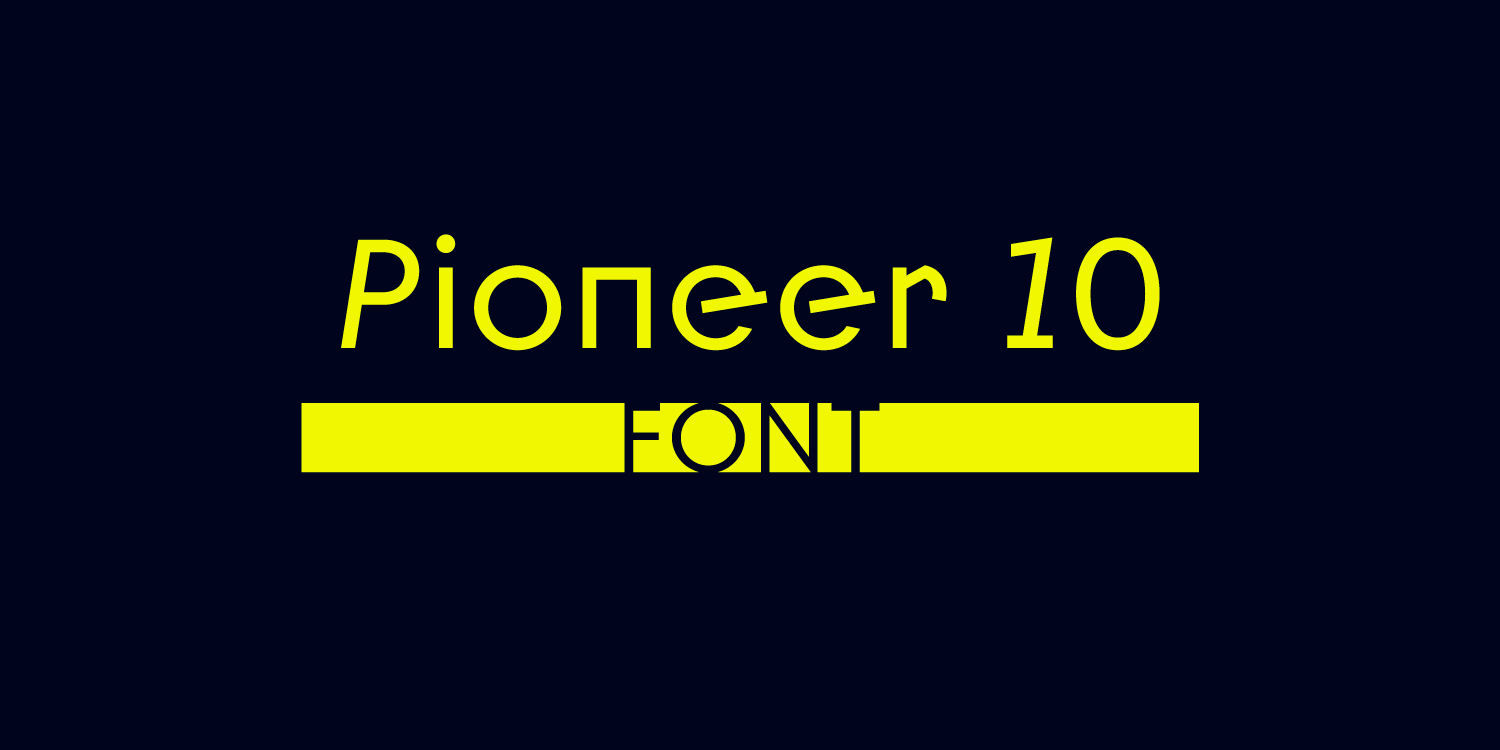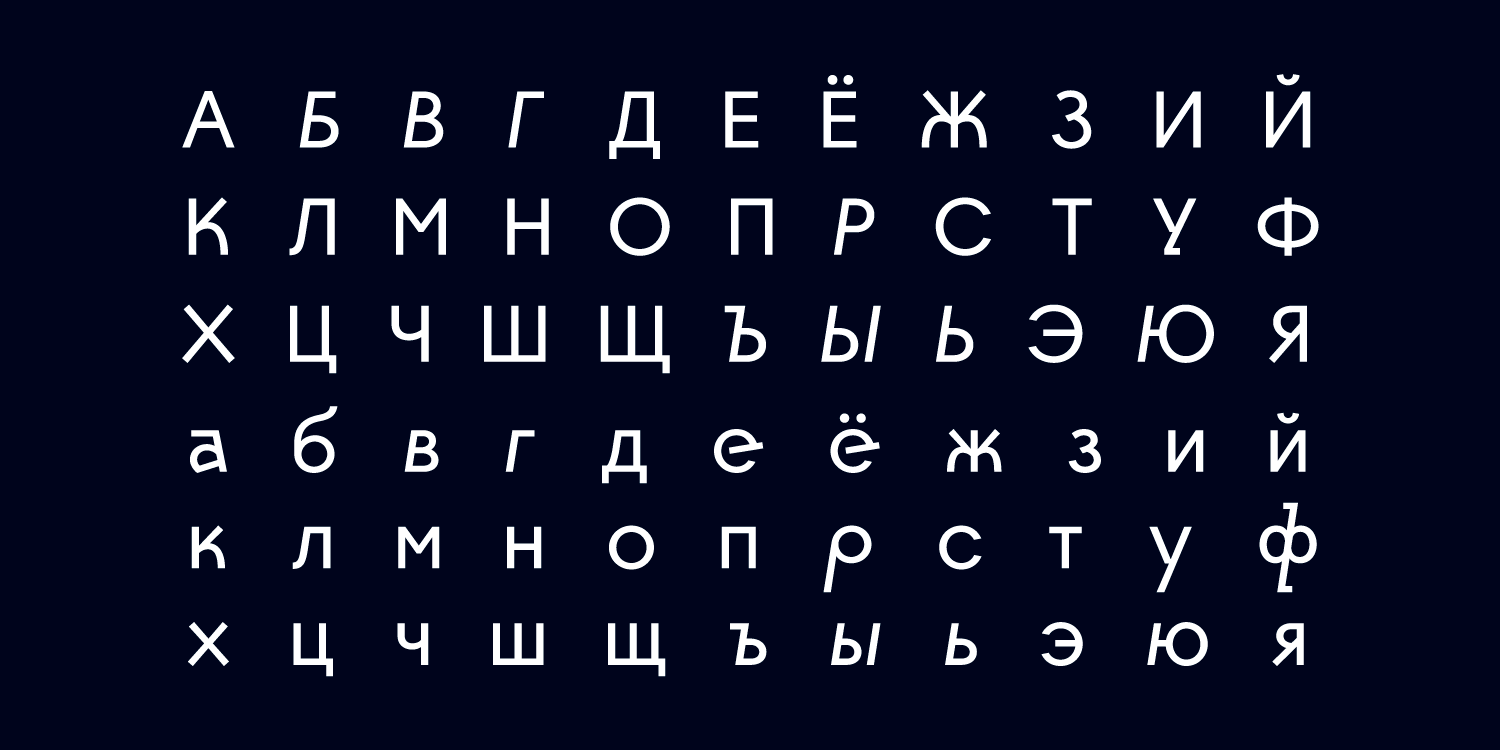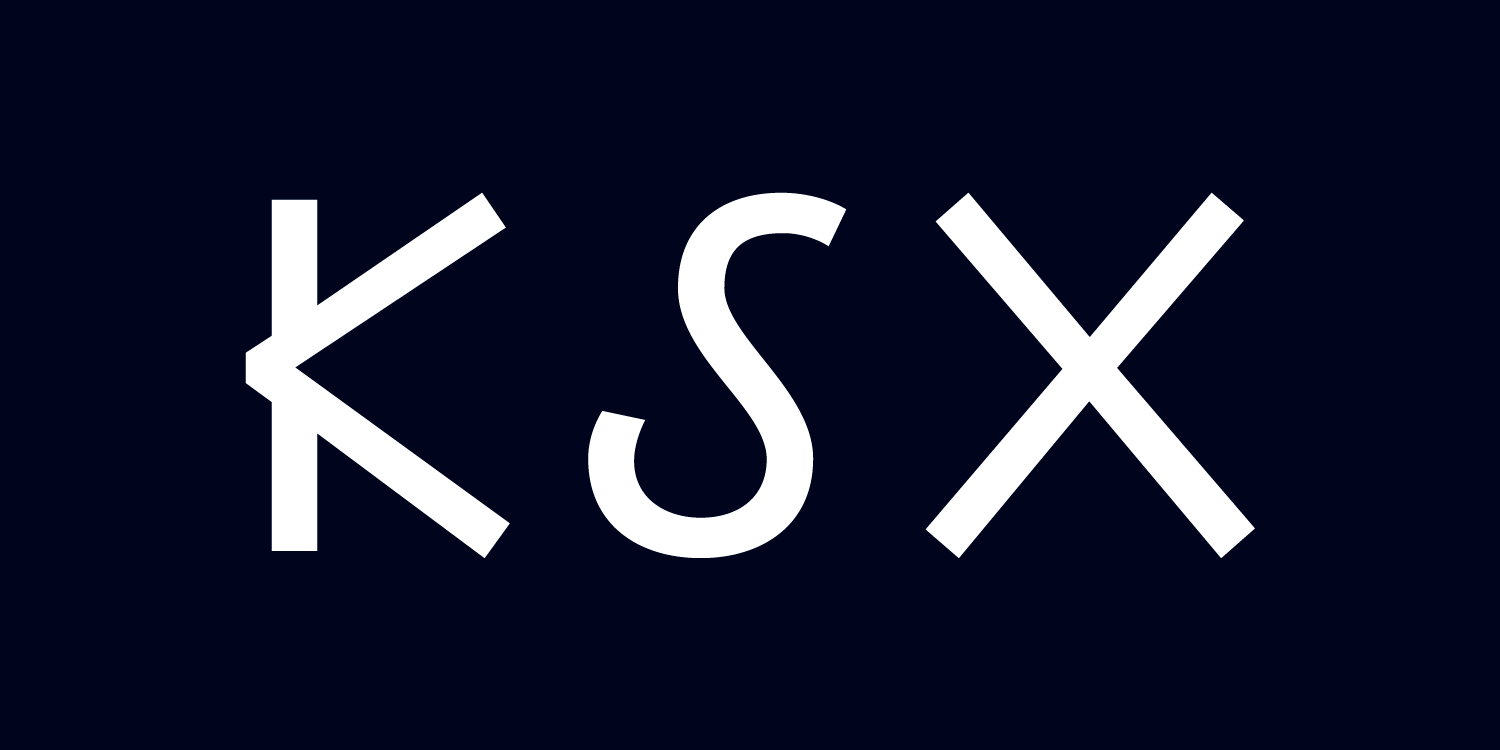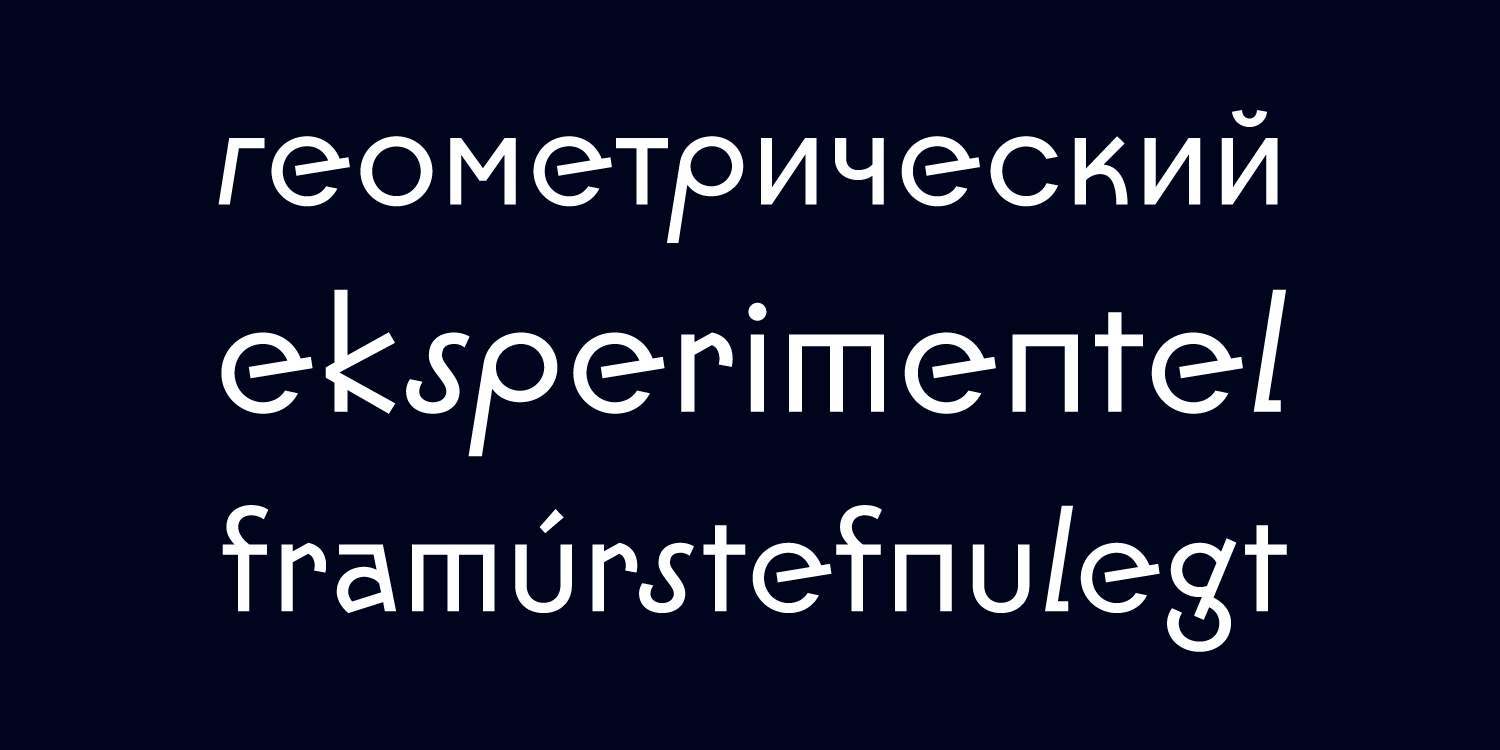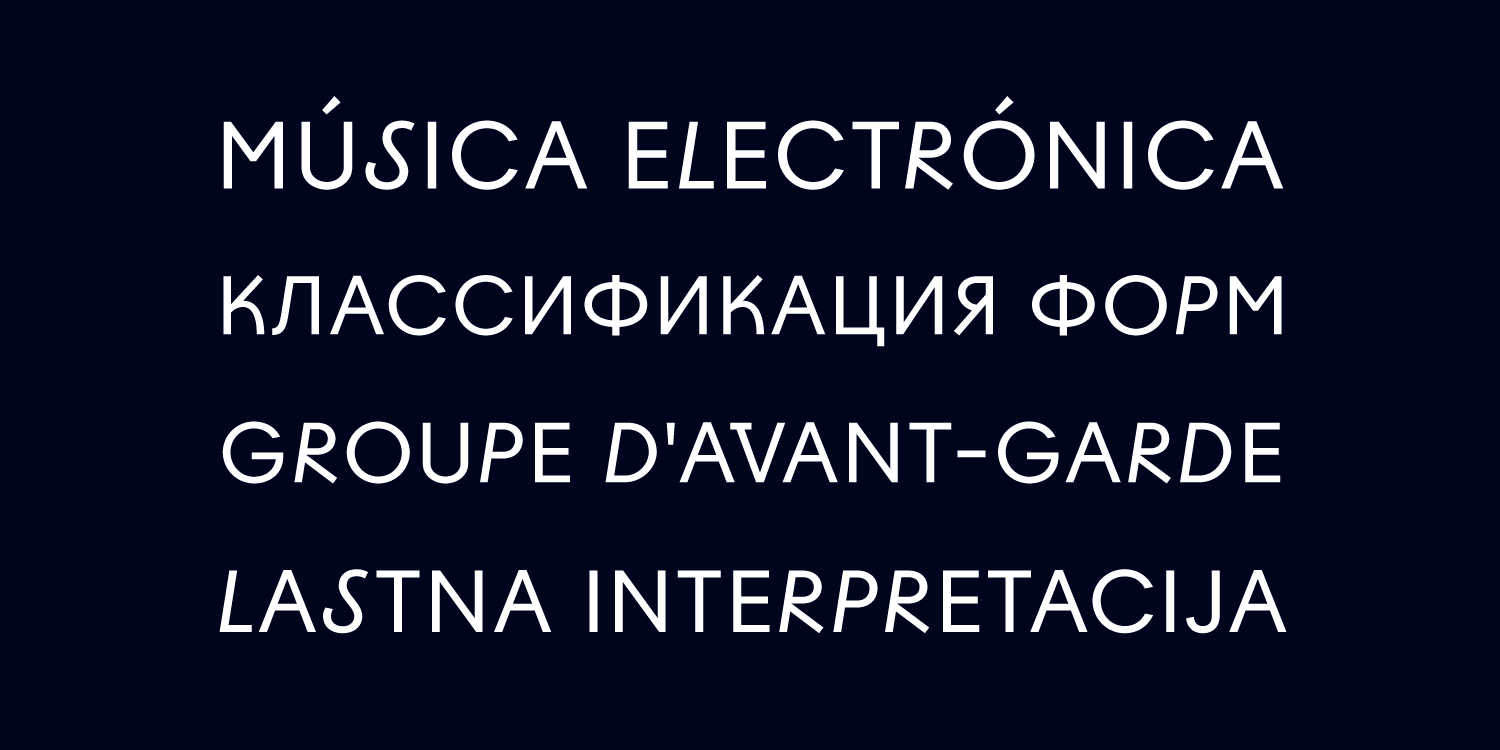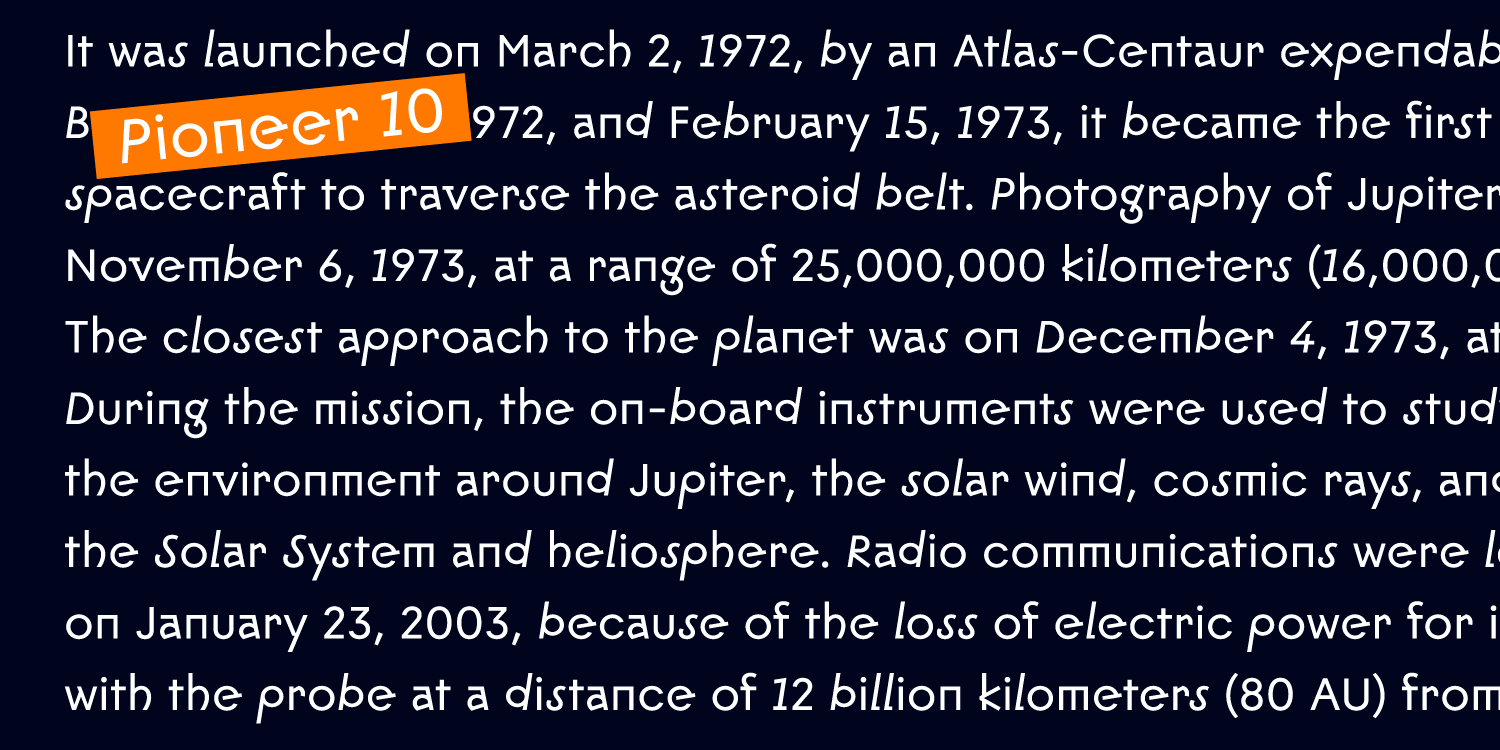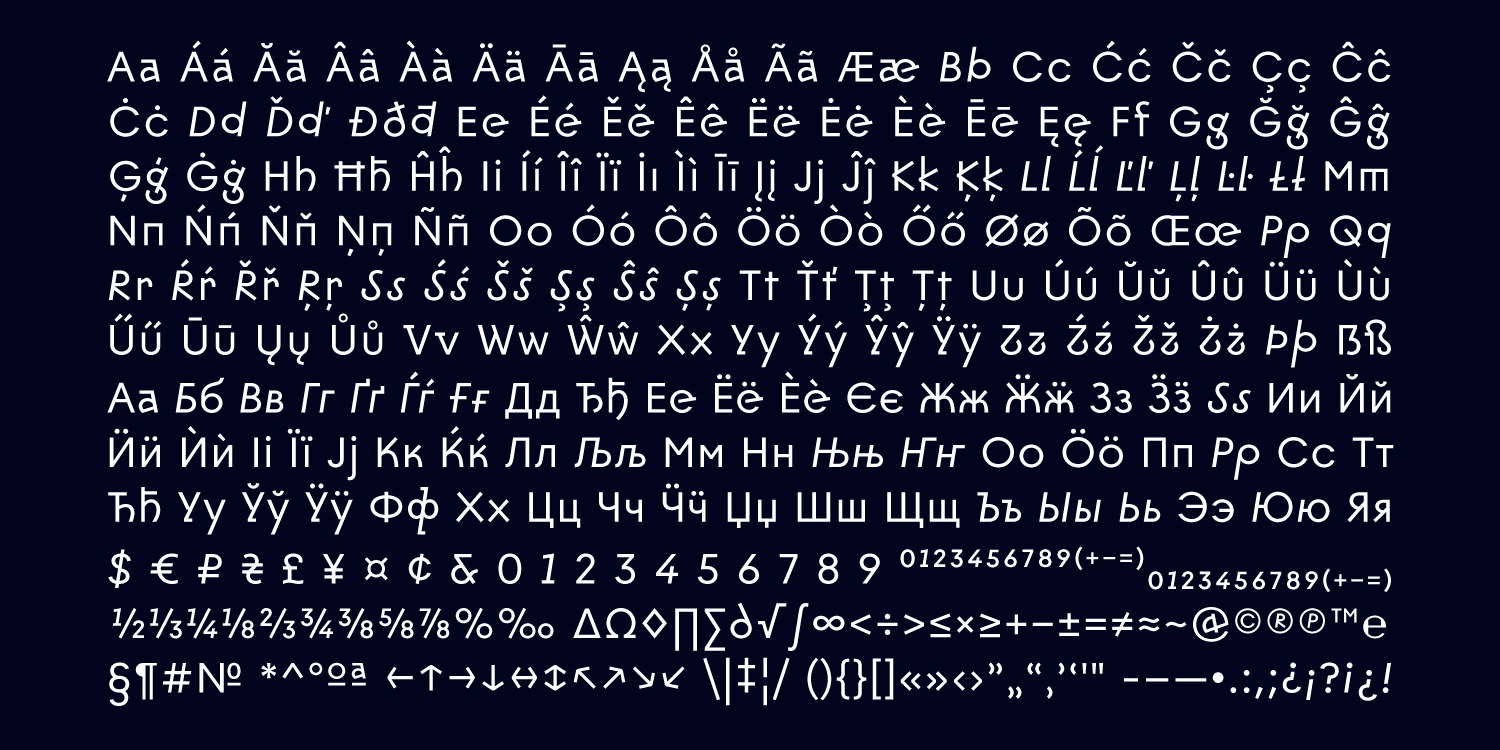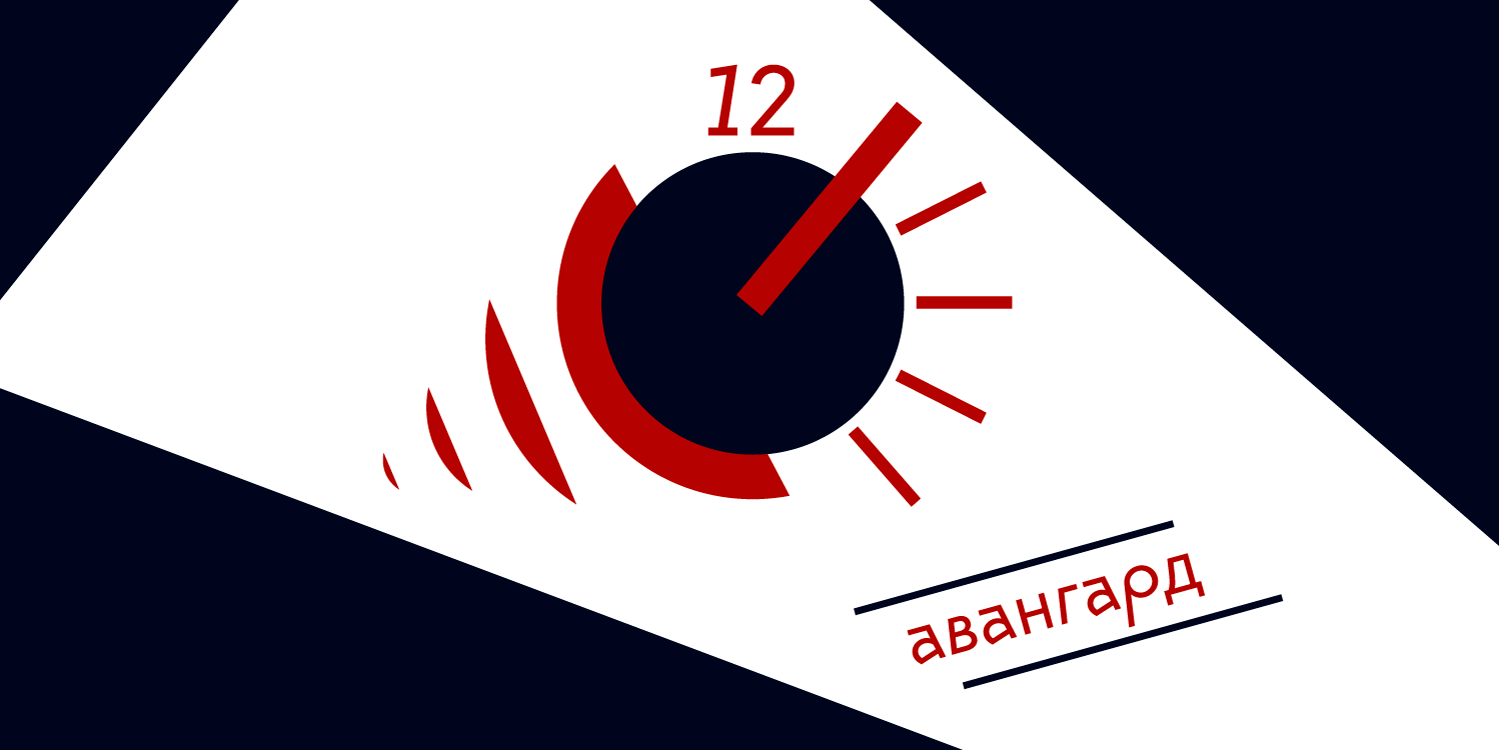
Pioneer 10 | font
Pioneer 10 - экспериментальный шрифт без засечек, сочетающий геометрические элементы прямого и наклонного шрифта. Идеей для его разработки послужили работы конструктивистов начала 20-ого века. Поддерживает кириллицу, расширенную латиницу и функции OpenType. Разработан в 2019 году.
Шрифтовой дизайнер Игорь Косинский